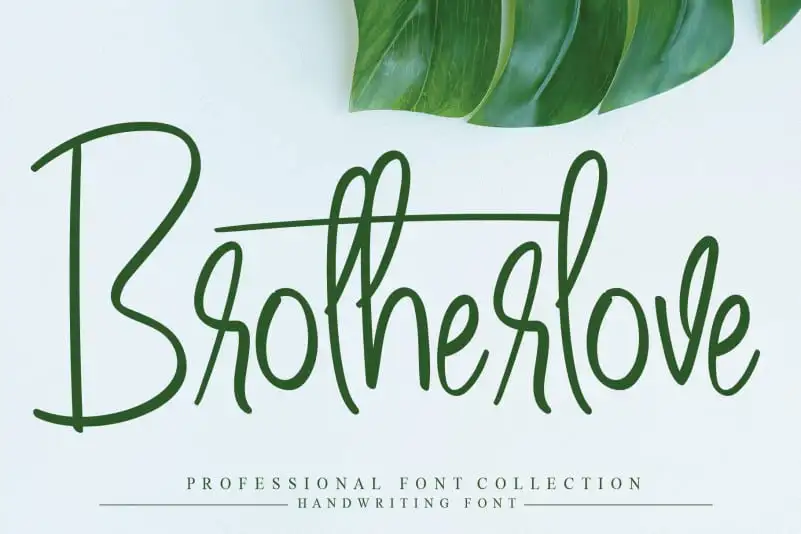
Brotherlove Script Font – Download Grátis
A fonte ‘Brotherlove Script Font’ é uma criação única do designer creativeletter, trazendo à tona a essência das fórmulas manuscritas. Ideal para aqueles que buscam dar um toque especial aos seus projetos de design, esta fonte oferece uma experiência singular e impressionante. Ela não apenas reforça o poder criativo do seu trabalho final, mas também proporciona uma conexão emocional profunda através da sua escrita única e vibrante. Em um mundo cada vez mais digitalizado, ‘Brotherlove Script Font’ traz uma pitada de serenidade à sua mesa de trabalho, oferecendo a você uma fonte que não só destaca seu design, mas também reflete parte do seu estilo pessoal. Tornando-se um membro inseparável da sua coleção de recursos gráficos de alta qualidade.